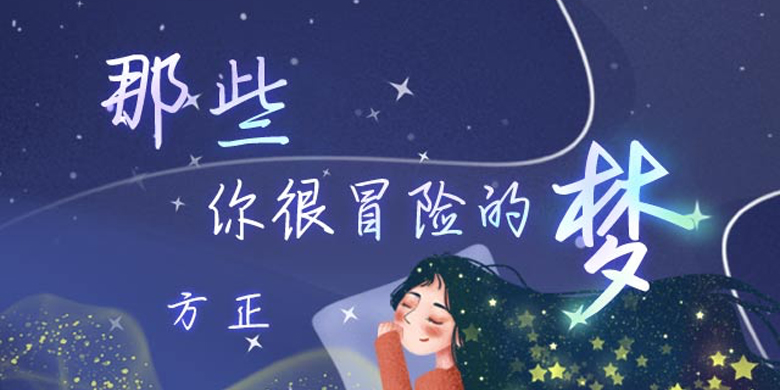
方正手迹-那些你很冒险的梦
字体品牌: 方正手迹 设计师:尚正中 字体分类:创意书写 字体属性:精品字 字符集:大陆简体(GB2312-80) 发布时间: 2020
该字体结构大气,行笔大胆,线条富于变化。近似日常书写的风格,看似随意,却有着既亲切又有行云流水般的写意书风。单字的结构舒展挺拔,排列在一起,舒适感极强。适用于文艺类的书刊、品牌广告和产品包装设计,以及社交网络的个性化用字。